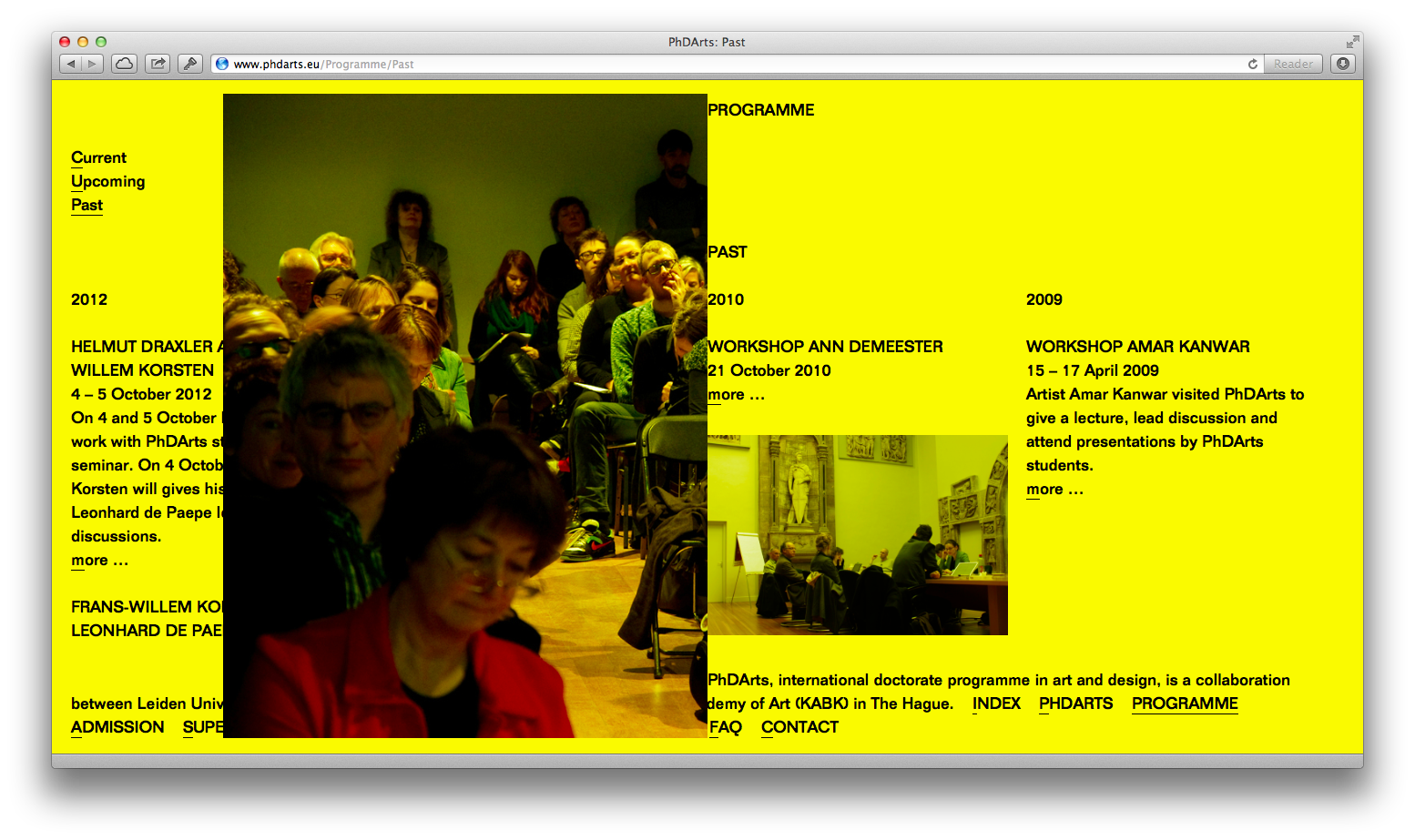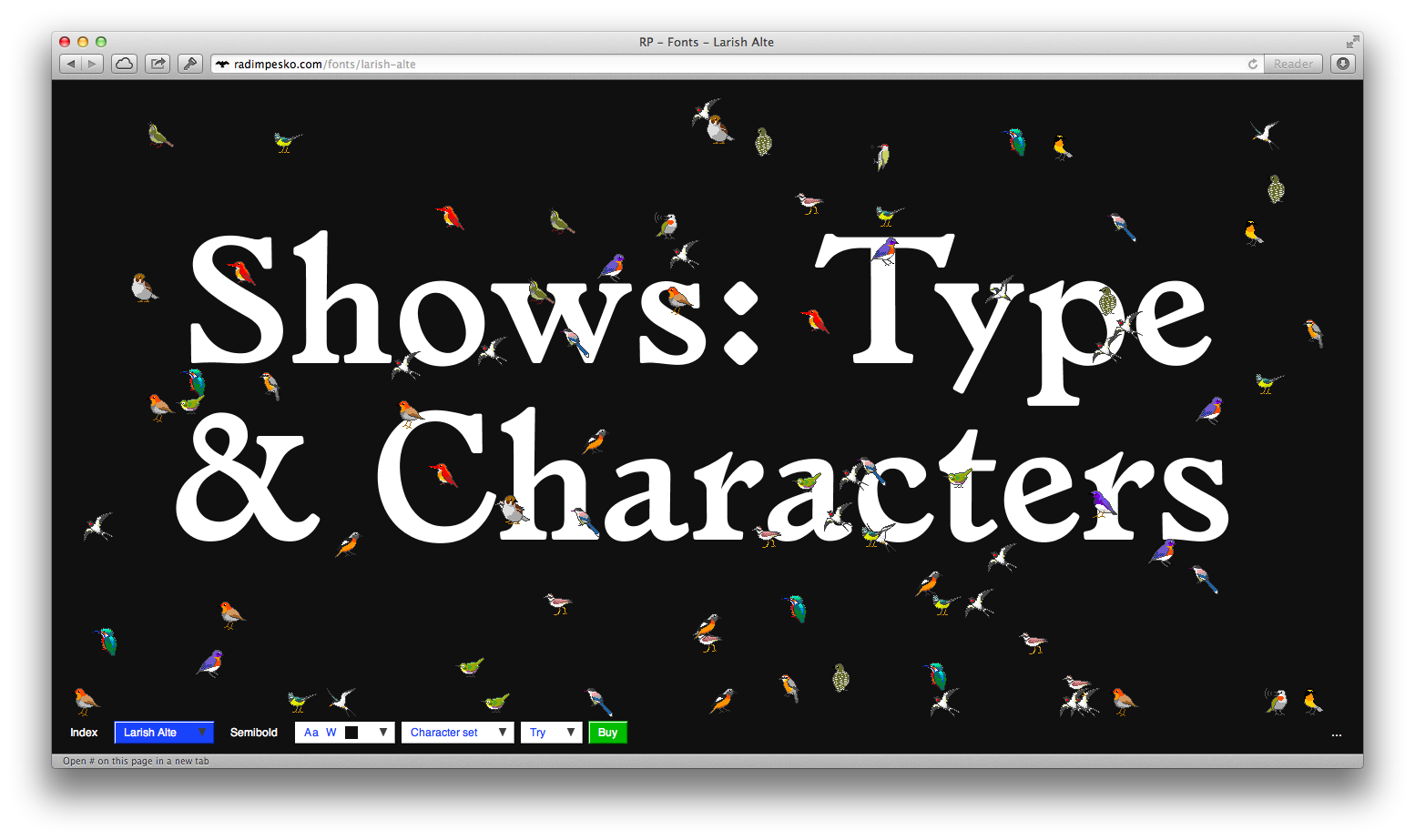
28. Seminář UGD: Typografie na webu
Přednášející, grafický designér Tomáš Celizna, rozebere specifika typografie na webu a potažmo v digitálních médiích obecně. Bude se věnovat rozdílům mezi typografií tradiční a webovou (digitální), a zaměří se na důsledky, které z jejich odlišností vyplývají. Akce proběhne v pondělí 19. listopadu od 19 hodin v HUBu Praha.
PhDArts, website, 2012, design: Tomáš Celizna a Mevis & van Deursen, programování: Tomáš Celizna
Grafický designér Tomáš Celizna (1977) působil v letech 2001 až 2005 společně s Petrem Knoblochem v Praze pod hlavičkou dgú. Mezi klienty jejich studia patřili mezi jinými A69 architekti, Moravská galerie v Brně nebo Uměleckoprůmyslové museum v Praze. V letech 2005–06 a 2008–09 byl designérem ve firmě Method Inc., nejprve v San Franciscu a poté v New Yorku. V Method pracoval mezi jinými na interaktivních projektech pro Autodesk, CNN nebo Google.
Prostřednictvím Fulbrightova stipendia (2006) absolvoval postgraduální studium grafického designu na Yale University School of Art v New Haven (2008).
V současné době žije a pracuje jako nezávislý designér v Amsterdamu. Poslední aktivity zahrnují práci pro Fakultu Architektury ČVUT v Praze, Graduate School of Design Harvard University v Cambridge, OASE Journal v Rotterdamu, Royal Academy of Art v Haagu a Sandberg Instituut v Amsterdamu.
Od roku 2011 působí jako lektor grafického designu na Gerrit Rietveld Academie v Amsterdamu. Od téhož roku je členem organizačního výboru Mezinárodního Bienále grafického designu Brno.
RP Digital Type Foundry, website, 2010, design: Tomáš Celizna a Radim Peško, programování: Tomáš Celizna